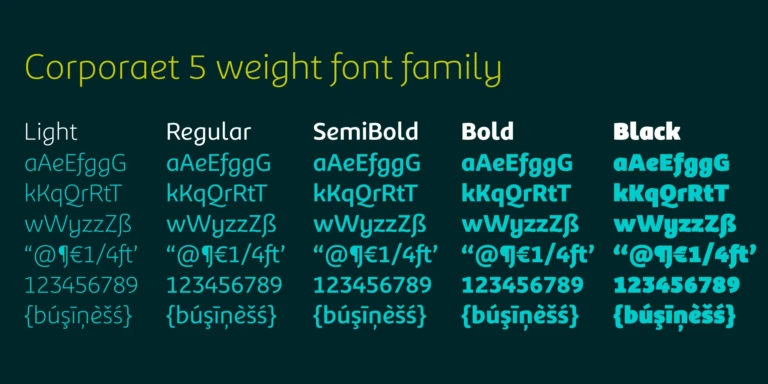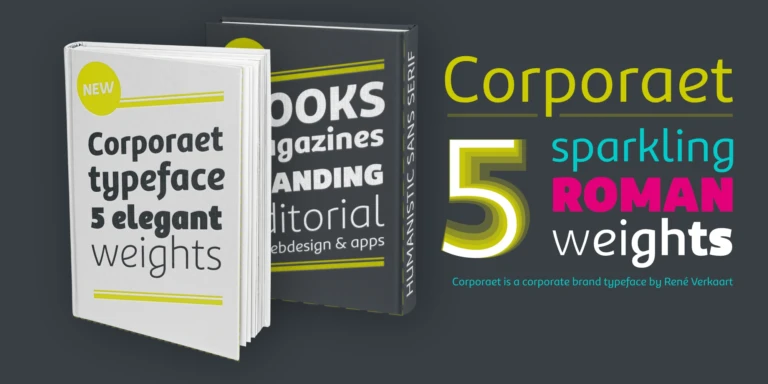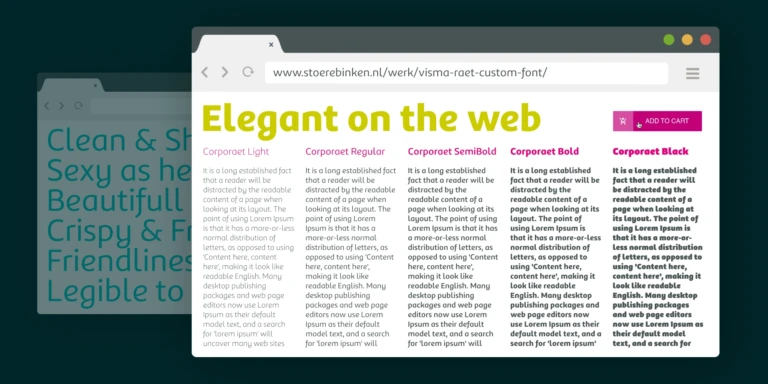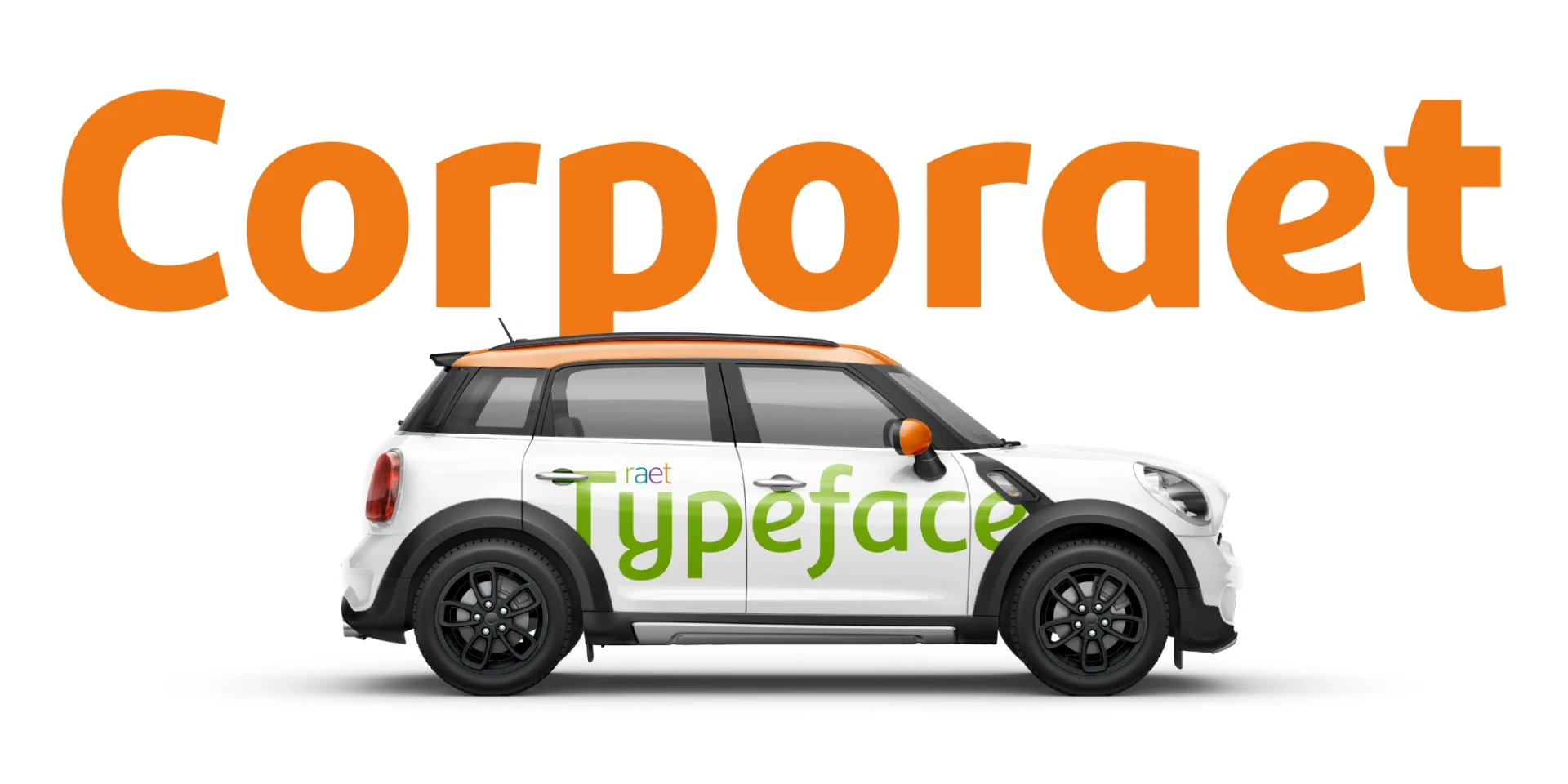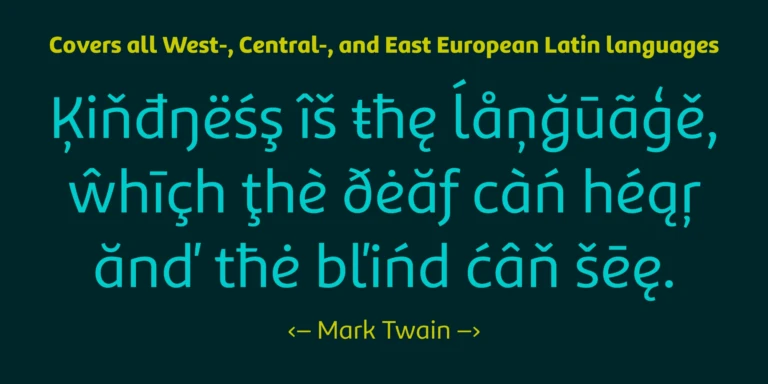
Visma | Raet custom font
Het Visma | Raet custom font “Corporaet” is het brandfont van de internationale HR-softwarespecialist Visma | Raet. Zij zijn het bedrijf dat HR-software in de cloud ontwikkeld heeft, waar mer dan 1,7 miljoen medewerkers dagelijks gebruik van maken. De custom font familie zorgt voor een consistente look en feel voor alle touch points in alle talen.
René created a font family that fits Raet very well
For the Raet brand, the font is a very important element, besides the colors and the photography. René has managed to create a font family that fits very well with the other pillars and that communicates our brand in very good way. You cannot create that if you do not listen carefully and look at all aspects of a brand, and that’s exactly what René did. He then made the perfect translation to our own Raet fonts. I can highly recommend René if you are looking for an expert who can translate your brand identity to a font.
Corporaet in use
Corporaet gewichten en stijlen
Corporate is verkrijgbaar in 5 Roman gewichten om een consistente merkidentiteit op elk touch point te garanderen, van website, apps, print, tv, uitzendingen tot alle mogelijke marketingproducten.
OpenType features
Corporaet bevat veel slimme OpenType features voor een soepele toepassing op de verschillende platforms en media. Til je corporate branding naar een hoger niveau met deze uitgebreide font familie.
- Denominators
- Fractions
- Lining Figures
- Numerators
- Standard Ligatures
- Tabular Figures
Taalondersteuning
Visma | Raet is een wereldspeler met vestigingen in Europa en Latijns-Amerika. Daarom bevatten de fonts alle West-, Centraal- en Oost-Europese Latijnse talen voor de landen waarin Visma | Raet actief is.